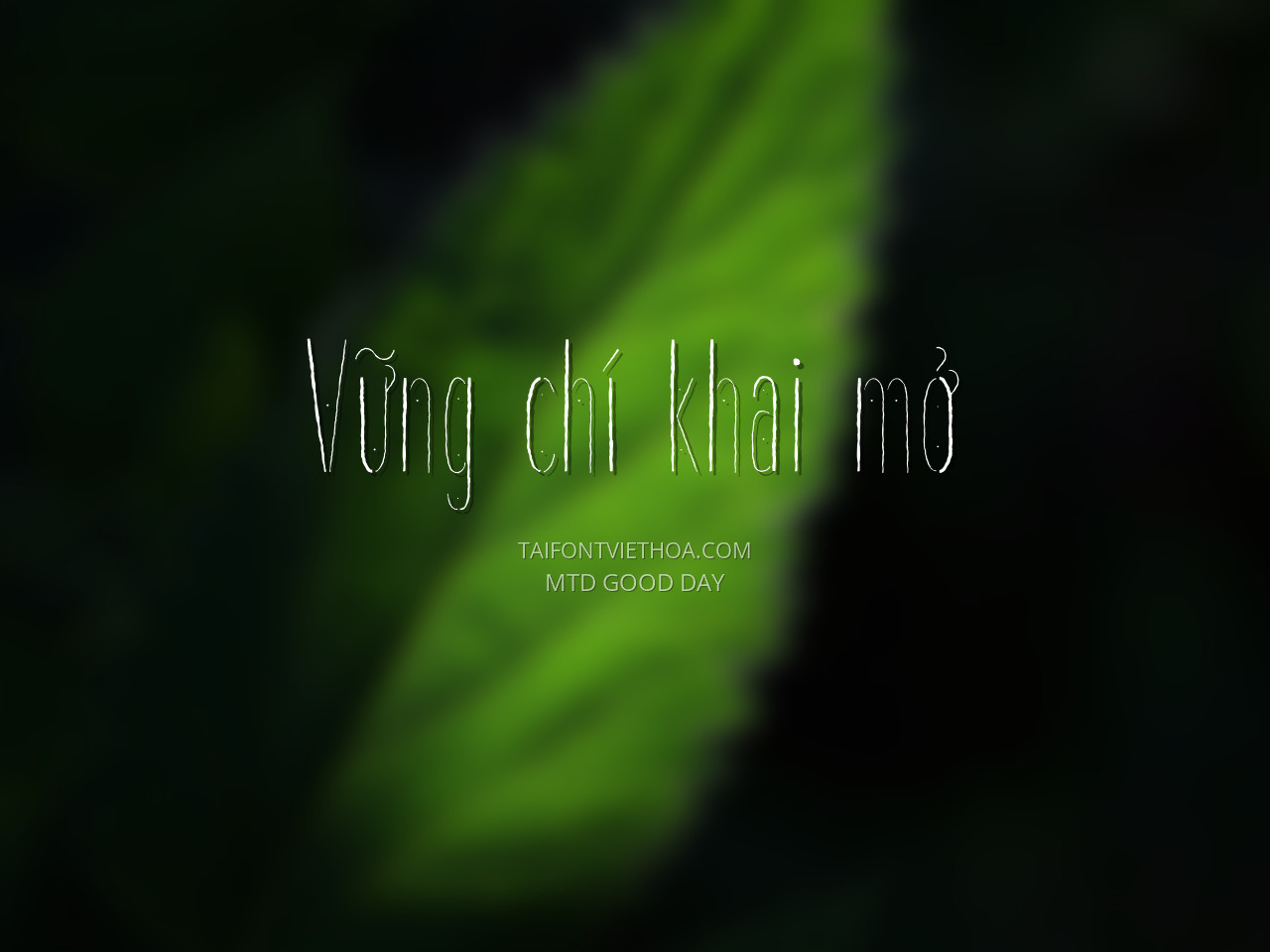
Font việt hóa MTD Good Day
Giới thiệu về font Good Day
Good Day là một font chữ viết tay hiện đại, mang đậm phong cách ngẫu hứng, năng động và tràn đầy cảm xúc, được thiết kế bởi Motokiwo Type (MTD). Font tái hiện chân thực nét bút tay tự nhiên, như những dòng chữ viết vội nhưng vẫn giữ sự tinh tế trong từng nét uốn. Với sự đơn giản trong cấu trúc và tính cá nhân cao, Good Day là lựa chọn hoàn hảo cho các thiết kế mang tính biểu cảm, gần gũi hoặc cần tạo ấn tượng chân thành. Phiên bản Việt hóa được thực hiện bởi chính MTD, hỗ trợ đầy đủ tiếng Việt và hơn 70 ngôn ngữ quốc tế.
Đặc điểm thiết kế và ứng dụng của font Good Day
Good Day sở hữu nét viết mềm mại, liền mạch và tự nhiên. Độ nghiêng nhẹ, các khoảng cách giữa các ký tự được tối ưu để tạo cảm giác chuyển động mượt mà và dễ đọc. Font đi kèm các ligatures cùng bộ ký tự thay thế phong phú, cho phép người dùng linh hoạt biến tấu tùy theo nhu cầu thiết kế. Với tone cảm xúc nhẹ nhàng, thân thiện, font này cực kỳ hiệu quả trong các ứng dụng mang tính cá nhân hoặc truyền cảm hứng.
Ứng dụng lý tưởng: thiết kế thiệp mời, trích dẫn cảm xúc, blog cá nhân, bìa sách, sản phẩm thủ công, bao bì mỹ phẩm handmade, thiết kế mạng xã hội hoặc bất kỳ nội dung nào cần đến sự chân thành và gần gũi. Ngành nghề phù hợp: wedding planner, giáo dục, quà tặng cá nhân, lifestyle, mỹ phẩm thủ công, thời trang nữ tính và các thương hiệu cá nhân hóa.